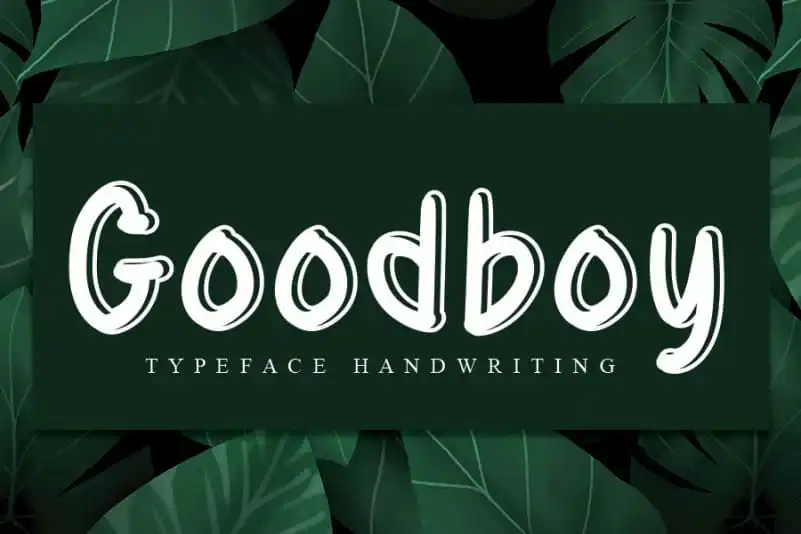
Goodboy Display Font – Download Grátis
A Goodboy Display Font é uma criação que simplifica a elegância para um único estilo de tipo que traz consigo uma autêntica impressão manuscrita. Seja para branding, headlines, designs de casamentos, convites, assinaturas, logotipos, etiquetas e muito mais – essa fonte oferece o nível mais alto de excelência em qualquer projeto. Seu design fluido e elegante proporciona um toque autêntico que se destaca entre as montanhas de tipografia disponível hoje. Com Goodboy Display Font, você pode criar elementos visuais que expressam criatividade e sofisticação sem perder a essência da comunicação visual. Através dessa fonte moderna e sofisticada, você transformará qualquer projeto em um verdadeiro destaque.